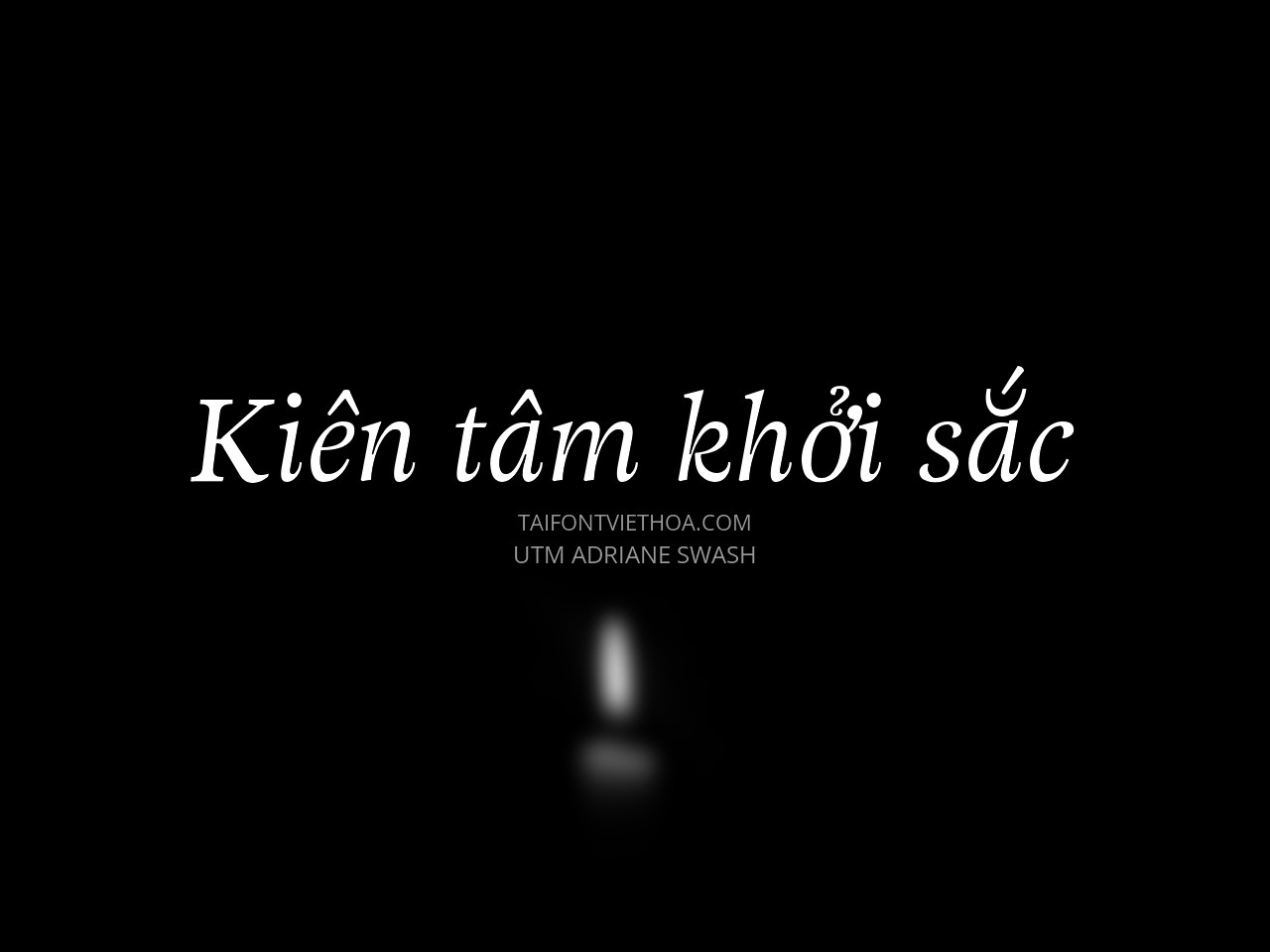
Giới thiệu về font UTM Adriane Swash
UTM Adriane Swash là phiên bản Việt hóa từ font gốc Adriane Swash – một biến thể thanh lịch thuộc họ chữ Adriane, được thiết kế bởi Marconi Lima (Typefolio Digital Foundry). Adriane Swash mang phong cách serif cổ điển pha trộn với các đường nét bay bổng, đặc trưng bởi các ký tự có đuôi kéo dài (swash) đầy tinh tế. Font được tạo ra để phục vụ các thiết kế sang trọng, biên tập cao cấp và các tác phẩm mang yếu tố nghệ thuật. Bản gốc được phát hành vào khoảng năm 2006–2008 và hỗ trợ hơn 200 ngôn ngữ bao gồm cả tiếng Việt, nhờ vào hệ ký tự Latin mở rộng.
Phiên bản UTM Adriane Swash do Đinh Kiên Việt hóa, đảm bảo khả năng hiển thị tiếng Việt một cách tinh tế và đồng bộ với tinh thần nguyên bản. Font được chia sẻ bởi taifontviethoa.com – nơi tập hợp những bộ font chất lượng cao đã được sàng lọc và kiểm duyệt bởi cộng đồng thiết kế chuyên nghiệp. Với tính ứng dụng cao trong các dự án cần sự trang nhã và cổ điển, UTM Adriane Swash là công cụ đắc lực cho các designer Việt.
Đặc điểm thiết kế và ứng dụng của UTM Adriane Swash
UTM Adriane Swash thuộc nhóm serif kết hợp swash – với cấu trúc có chân chữ mềm mại, độ tương phản cao giữa các nét dày mảnh, cùng các ký tự có đuôi bay lượn nghệ thuật. Font thể hiện rõ sự thanh lịch, truyền thống và lãng mạn trong từng chi tiết, phù hợp cho các tiêu đề nổi bật, thương hiệu cao cấp hoặc ấn phẩm biên tập chuyên nghiệp.
Font lý tưởng cho các ứng dụng như: thiết kế sách, bìa tạp chí, thiệp mời, logo mỹ phẩm, thiết kế tiệc cưới, bao bì sang trọng, hoặc dự án branding trong ngành thời trang cao cấp. Các ngành nghề phù hợp gồm: truyền thông sáng tạo, mỹ thuật, biên tập xuất bản, tổ chức sự kiện và thời trang cao cấp.